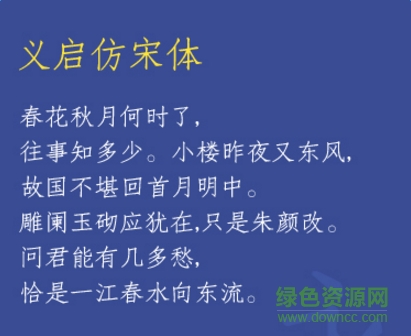
義啟仿宋體字體
義啟仿宋體是一款義啟類手寫風(fēng)格字體軟件,仿宋體以布局整潔優(yōu)美的整體效果,給人非常正式有章法的感覺,適合比較有創(chuàng)意的海報廣告標(biāo)題內(nèi)容應(yīng)用,也深受廣大書法家的喜愛,還有更多好看字體盡情期待,歡迎到綠色資源網(wǎng)下載體驗!
字體介紹
工信部四大標(biāo)準(zhǔn)字體:宋、仿宋、楷、黑。仿宋體,是一種采用宋體結(jié)構(gòu)、楷書筆畫的較為清秀挺拔的字體,筆畫橫豎粗細(xì)均勻,常用于排印副標(biāo)題、詩詞短文、批注、引文等,在一些讀物中也用來排印正文部分。 在宋、仿宋、黑、楷四正體中,仿宋氣息最接近手寫。章法氣息更加靈動。義啟仿宋體更是放大這一特點,整體布局律動好看!